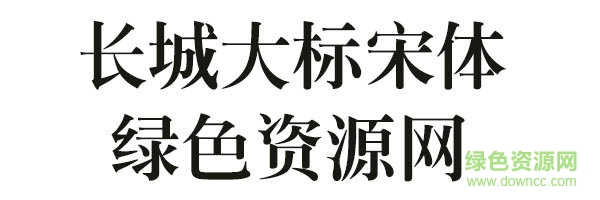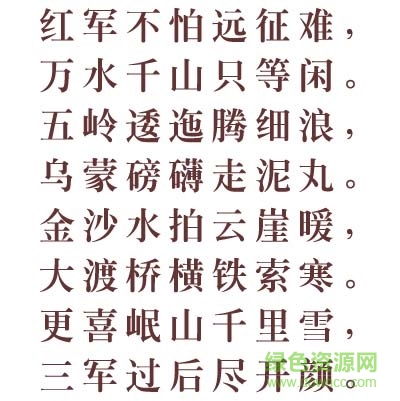
長(zhǎng)城大標(biāo)宋體是一款標(biāo)準(zhǔn)的宋體簡(jiǎn)體字體,整體筆畫(huà)偏粗,win10系統(tǒng)也可以使用,喜歡的朋友,趕快到綠色資源網(wǎng)下載體驗(yàn)吧!
長(zhǎng)城大標(biāo)宋體整體效果看起來(lái)會(huì)顯得特別的高大,點(diǎn)、撇、捺都特別的有氣勢(shì),顯得特別的大氣玩美。